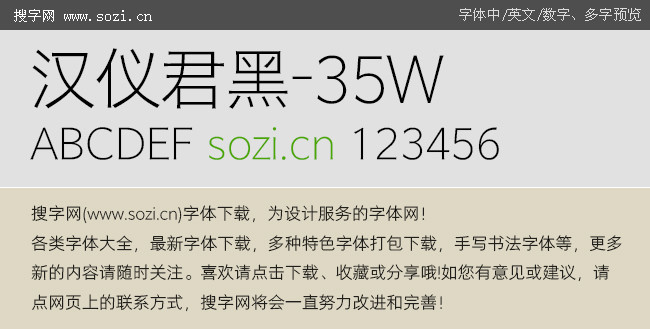
漢儀君黑-35W
搜字網給大家提供一款漢儀君黑-35W中文字體下載,漢儀君黑-35W字體是一款擁有喇叭口的字體,漢儀君黑字體的筆畫設計在傳統黑體的基礎上,控制了起筆收筆的“喇叭口”張度,使其逐漸向現代黑體發展,更加適合正文排版使用,提高了用戶的閱讀體驗。與現代黑體對比來看,漢儀君黑的曲線感增強,筆意舒展,細節融入了更多人文氣息,優雅且更具親和力。與傳統黑體比較而言,漢儀君黑字形略扁,黑白空間比例飽滿且適宜閱讀,讓字體在更小的空間內得以清晰展示。(本字體為個人非商用版,如需要商用請聯系漢儀公司購買版權)